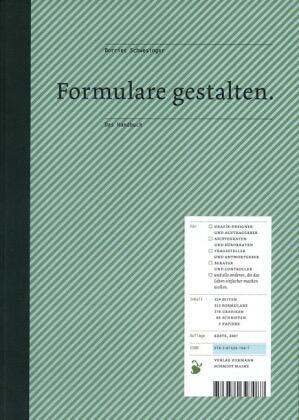
Formulare gestalten
Kaum ein anderes Medium kostet seine Benutzer, Leser und Entwerfer so viel Nerven und Zeit wie Formulare. Ob Rechnungs-, Antrags- oder Bestellformular: Mit viel Aufwand werden in Ämtern und Unternehmen täglich tausende Formulare erstellt, bearbeitet, weggeschickt und abgeheftet. Und trotz viel Mühe von den Kunden kaum verstanden und nur halb ausgefüllt. Formulare prägen das Erscheinungsbild von Unternehmen und öffentlichen Verwaltungen – leider oft nachhaltig negativ.
»Formulare gestalten« zeigt wie wichtig gut gestaltete und verständliche Formulare sind, die den Kunden nützen und nicht frustrieren.
»Formulare gestalten« ist das Handbuch zur Formulargestaltung. Es hilft systematisch beim Gestalten, ist Nachschlagewerk und umfangreiche Sammlung vieler guter Beispiele gelungener Formularkonzepte.
»Formulare gestalten« richtet sich an professionelle Gestalter sowie Anwender in Unternehmen und Verwaltungen, die Formulare für ihre tägliche Arbeit benötigen und erfolgreicher mit ihren Kunden, Partnern und Mitarbeitern kommunizieren wollen.
Rezension
Eine Landkarte für Amtsschimmel.
Der Designer entwirft den Dialog zwischen Mensch und Verwaltung: Ein Handbuch zur Formulargestaltung
von Martin Z. Schröder
Welche Drucksache erregt am ehesten Unwilligkeit? Das am wenigsten gemochte bedruckte Papier ist das Formular. Es belegt einen Unterschied an Macht, es tritt autoritär auf, es zwingt seinen Benutzer in eine einzige Rolle und weist ihm eine einzige Bedeutung zu. Ein Formular ist starrer Teil eines Dialoges, an dem der Benutzer nach gegebenen Regeln teilnimmt oder nicht. Beeinflussen kann er ihn kaum.
Formulare werden größtenteils von Behörden verwendet, die es bislang selten für nötig hielten, dem Individuum das triste Zwiegespräch aus Frage und Antwort auf vorgedruckten Linien und in anzukreuzenden Kästchen leicht oder sogar verständlich bis angenehm zu machen. Formulare waren bis heute kaum Gegenstand schöpferischer Arbeit von Typografen und Designern. Schon lange ist das Formular auch in die Wirtschaft vorgedrungen. Kunden müssen in standardisierter Form Informationen nennen, um überhaupt Verbindung zu einem Unternehmen aufnehmen zu können.
Einen Studenten des Kommunikations-Designs an der Fachhochschule Potsdam hatte das Thema derart gefangen, daß seine Diplomarbeit den Verlag Hermann Schmidt Mainz von der Idee überzeugte, ein Handbuch daraus zu machen: „Formulare gestalten“, geschrieben, entworfen und gesetzt von Borries Schwesinger, auf feines Papier untadelig gedruckt und vortrefflich in Halbleinen gebunden. Ein Musterbeispiel für ein Buch unserer Zeit, das Konventionen still aufnimmt und zugleich zum Leser unserer Tage spricht. Ein Typografie-Buch in guter Sprache, sauber und gepflegt entworfen, und mit Humor. Also ohne das witzelnde Anbiedern und das weit verbreitete redundante Animationsgehabe einer Design-Bohéme, die auf die Umhängetasche einer Tagung größeren Wert legt als auf die Vorträge.
Die Begeisterung von Borries Schwesinger für seine umfangreiche Arbeit ist so feurig, daß sie auf den Leser dieses Buches überspringen kann, auch wenn dieser kein Designer ist. Oder wenn er schon viele andere Bücher über Typografie gelesen hat.
Wir werden knapp bekannt gemacht mit den frühen vorgefertigten Urkunden des Mittelalters und den ersten gedruckten Formularen: Ablaßbriefen aus der Presse Gutenbergs. Wir sehen gepflegte Formulare, die Kurt Schwitters für die Stadt Hannover entworfen hat. Schwesinger beleuchtet das Formular als Gesprächsmedium und wie wir damit etwas beantragen, belegen, berechnen, berichten, beantworten, bescheiden, melden, erklären, quittieren, protokollieren, wählen, wie wir uns ausweisen und beurkunden lassen. Der Autor zeigt, daß ein Antrag auf einen französischen Führerschein nicht weniger scheußlich aussieht als der „Antrag auf Leistungen zur Sicherung des Lebensunterhalts nach dem Zweiten Buch Sozialgesetzbuch (SGB II) - Arbeitslosengeld II/Sozialgeld“ oder daß manche Versicherung und manche Bank ihre Kunden ebenso schmählich behandelt wie der Staat die Empfänger von Finanzhilfe. Die Formulare, die Schwesinger in Europa und Amerika eingesammelt hat, erinnern an eine Landkarte für Amtsschimmel. Dabei wird kein negatives Wort über die Bürokratie verloren, sie bildet immerhin eine Grundlage des demokratischen Staates, um seinen Bürgern möglichst vernünftig und effizient zu dienen. Und eben diesen Charakter, diese Deutung der Beziehungen zwischen Bürger und Institution kann ein gutes Formular sichtbar machen.
Wir lernen, daß der Designer nicht nur Kästchen umverteilt, sondern daß er sich hineindenkt in den Dialog zwischen Mensch und Verwaltung. Er entwirft kein Papier, sondern eine Beziehung. Er muß ein Dokument schaffen, das von beiden Seiten verstanden wird, und im günstigsten Falle ordnet der Designer die ganze Beziehung neu, beispielsweise vom Antrag zum Auftrag, und greift wohltuend in die Verwaltung ein.
Das Handbuch belehrt mit vielen Details über den guten Entwurf, zeigt Formular-Entwürfe für das Internet, und ein Kapitel ist der kommentierten Abbildung gelungener Arbeiten unserer Tage gewidmet. Dieses Werk nährt die Hoffnung, eines Tages ein Päckchen versenden zu können, ohne sich Gedanken über die „Vorausverfügung“ machen zu müssen und daß die Anmeldung eines Gewerbes oder eines Radios nicht schon beim Anblick der häßlichen Formularfratzen den Gefühlshaushalt blockiert. Möge dieses schöne Werk bald überall Verbreitung finden, wo der Mensch standardisiert sprechen soll, auf daß uns der Amtsschimmel freundlich anwiehert statt undeutlich Befehle zu kläffen.
Untertitel: Ein Handbuch
Autor(en): Borries Schwesinger